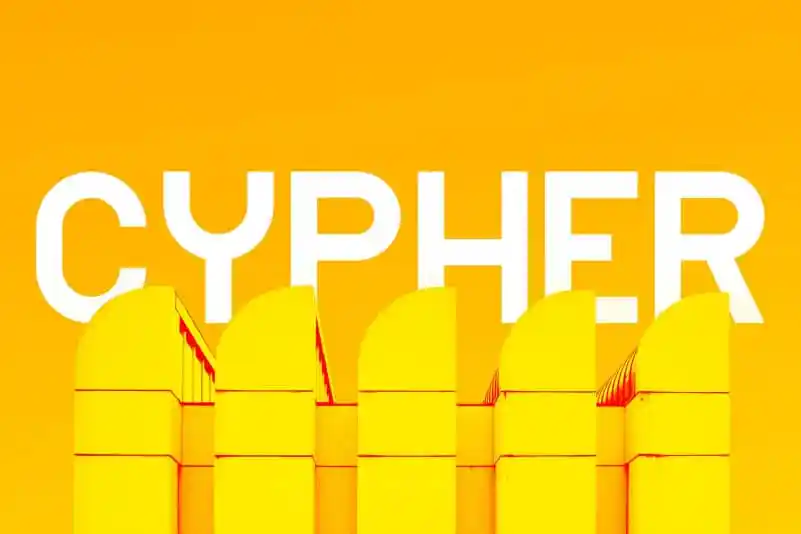
Cypher Sans Serif é uma família de tipo geométrica que incorpora influências diretamente do movimento Bauhaus. Esta elegante familia tipográfica compreende quatro tipos diferentes, cada um apresentando uma versão única e moderna do Cypher tipo. Através da fusão dos princípios fundamentais do Bauhaus nas formas de letra, este fonte atinge uma proporção ímpar de estilização e simplicidade, tornando-o perfeito para o design de logotipos ou logotipo, identidades de marca, gráficos publicitários, banners, postais, sinalizações, identidades corporativas e editoriais que são capazes de proporcionar uma identidade única. É um recurso poderoso para designers que buscam estilos claramente distinguidos. Cypher Sans Serif é perfeito para aqueles que valorizam a simplicidade pura em sua tipografia, mas desejam algo mais vibrante e moderno.